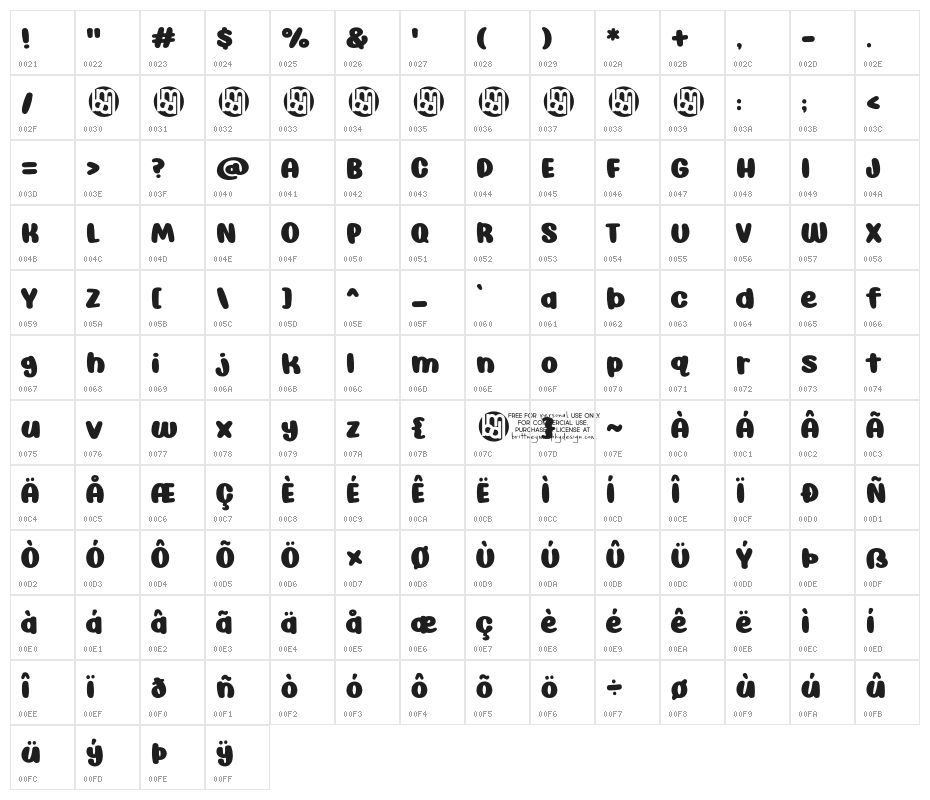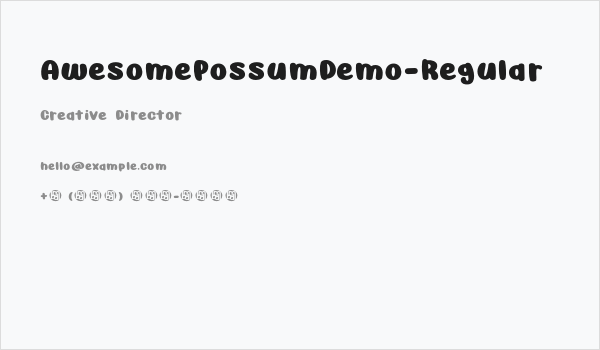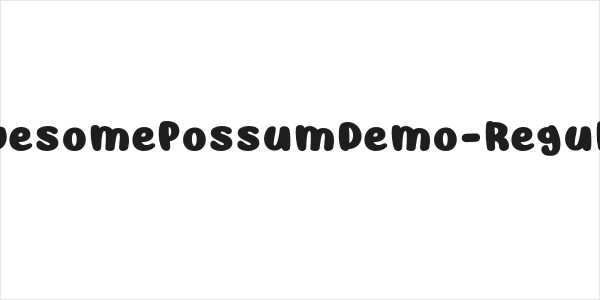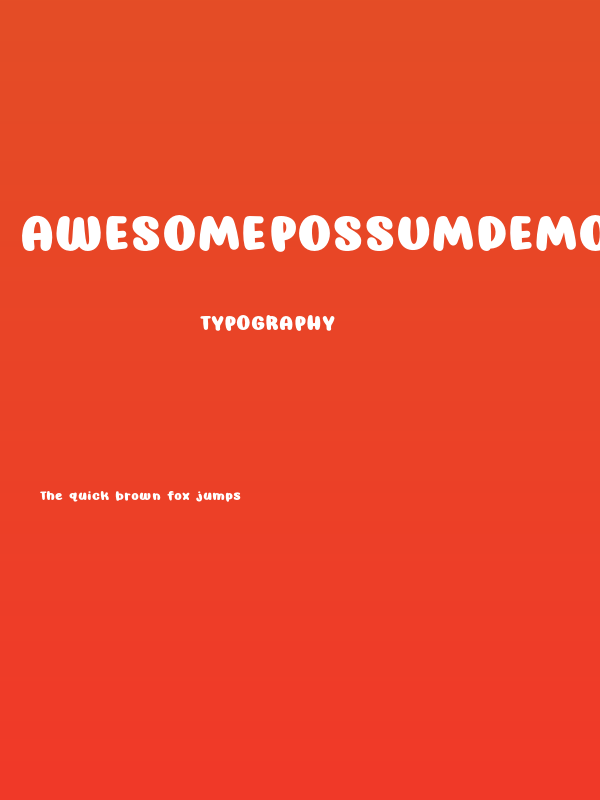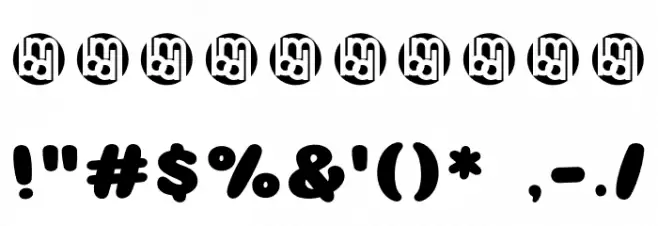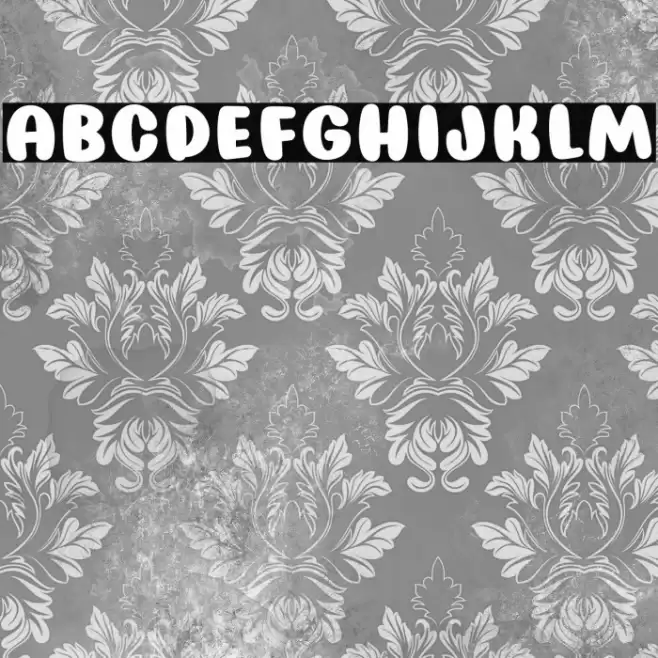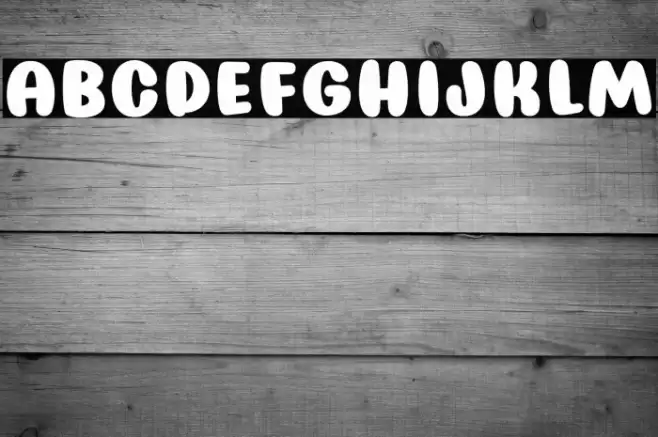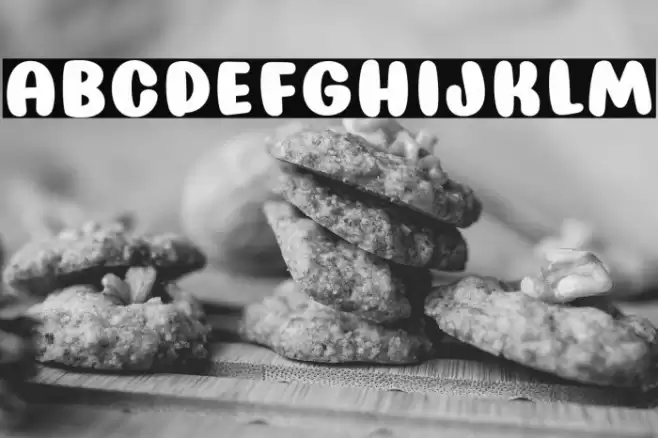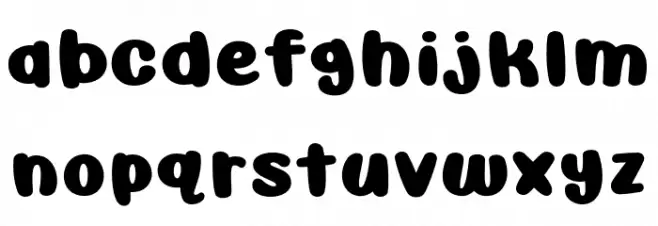
AwesomePossumDemo-Regular Font
| Style général | Playful |
| Projets proposés | Ideal for children's books, playful branding, party invitations, and creative posters. |